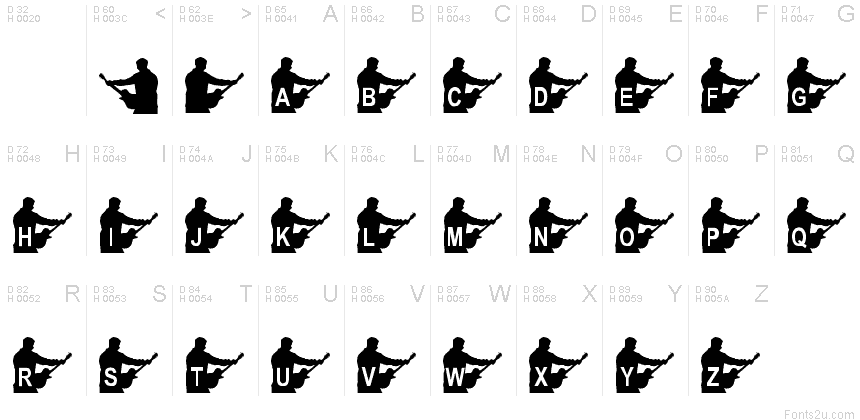
KR Steve's Solo autorstwa Kat z 2001 roku to darmowy, dekoracyjny krój displayowy, w którym główną rolę gra sylwetka gitarzysty. Każdy znak przypomina muzyka w trakcie gry, a litera jest wkomponowana bezpośrednio w jego postać, zamiast znajdować się obok.
KR Steve's Solo świetnie sprawdzi się na ulotkach zespołów, plakatach koncertowych, okładkach albumów, szyldach klubów muzycznych czy jako akcent w logo, ponieważ motyw gitary sam w sobie stanowi mocny przekaz wizualny. Nadaje się też do setlist, zaproszeń na wydarzenia i innych materiałów promocyjnych, w których potrzebujesz gotowego motywu muzycznego bez konieczności tworzenia pełnej ilustracji.